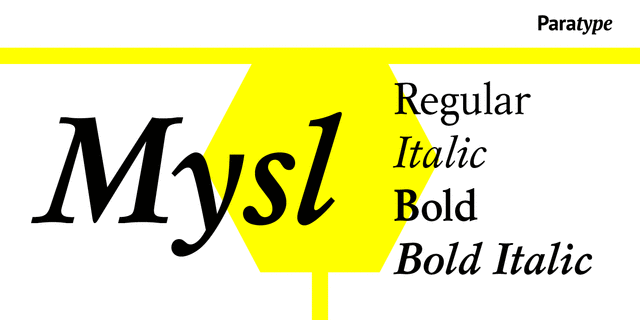
Шрифт разработан в наборном отделе шрифтов НПО Полиграфмаш в 1986 (дизайнеры Исай Слуцкер, Эмма Захарова) на основе шрифта Polytizdat, 1966 (дизайнер Вера Чиминова), по мотивам шрифта Claude Garamond, 16 век.
пафосный, благородный, консервативный, традиционный, классический, художественный, серебристый, образованный, мастерский, исторический, гуманитарный, комильфо, вежливый, архитектурный